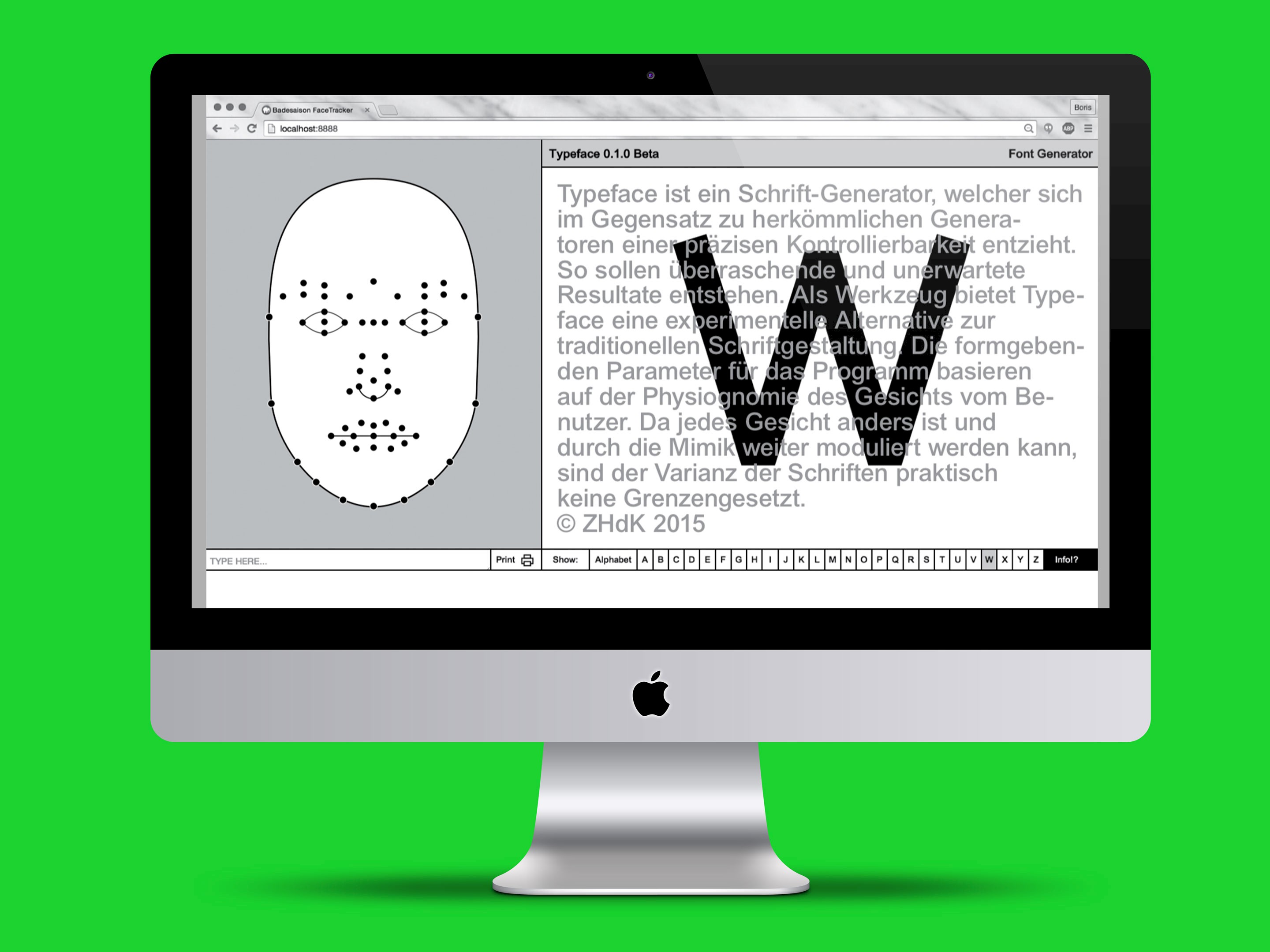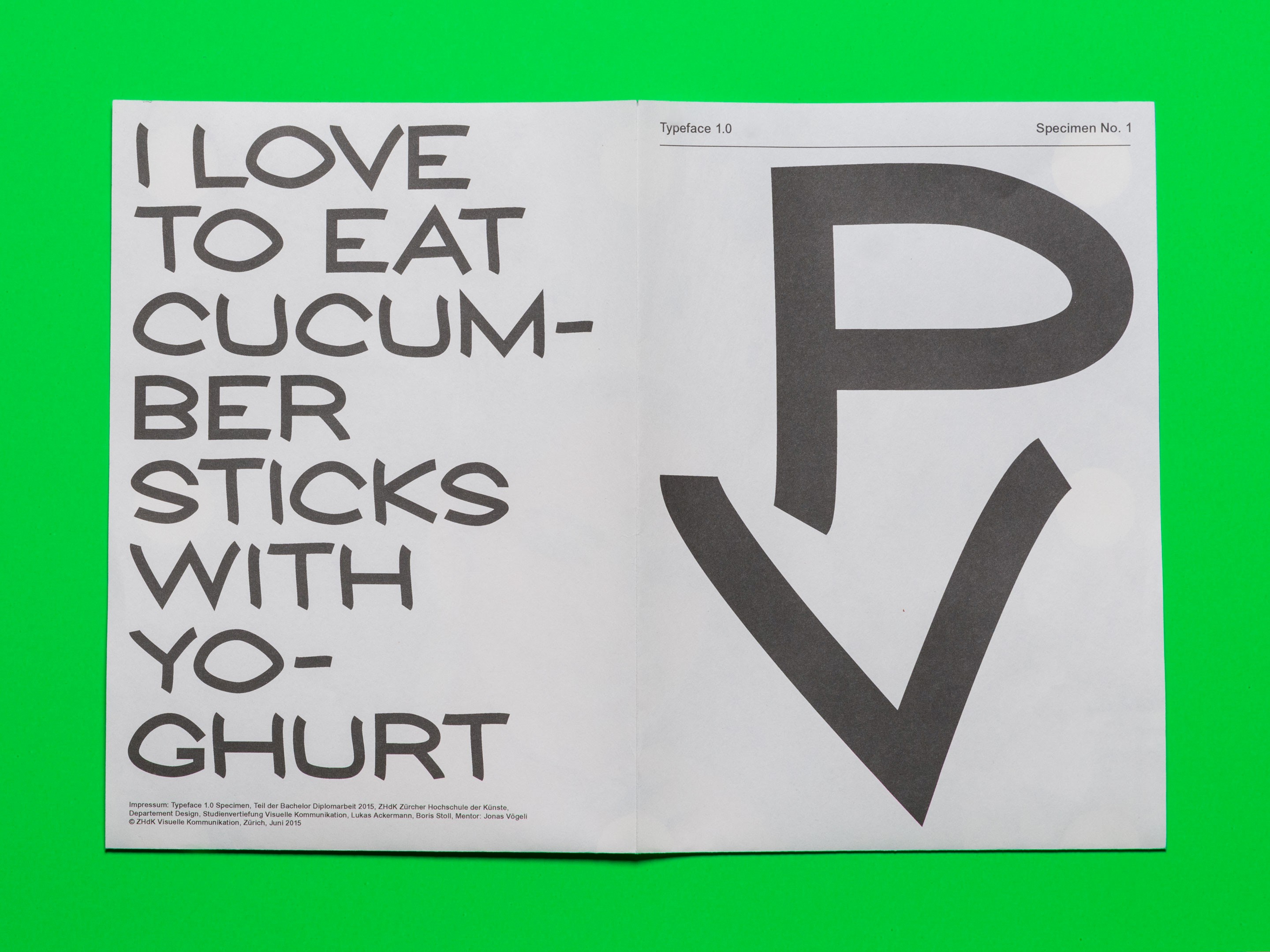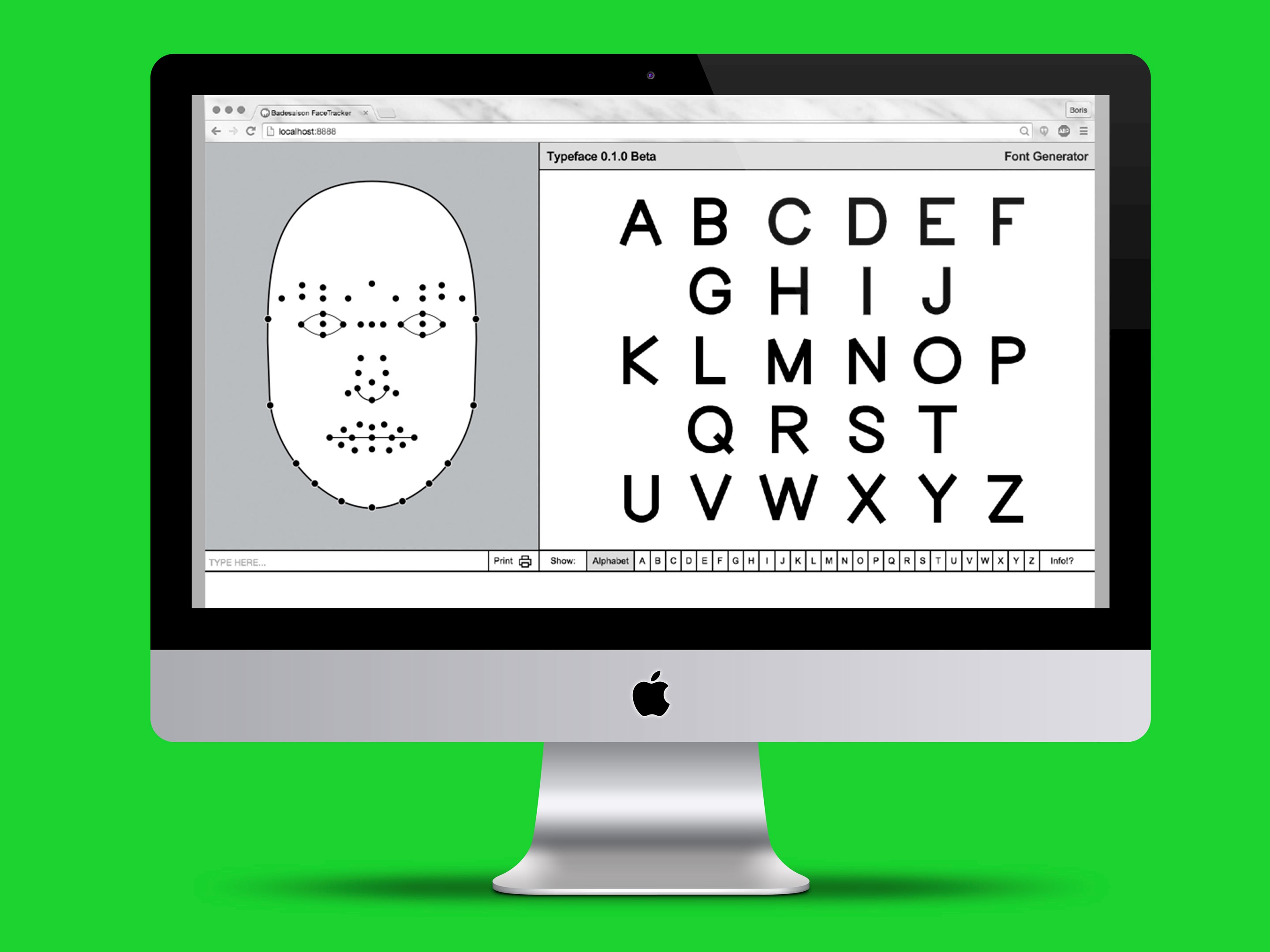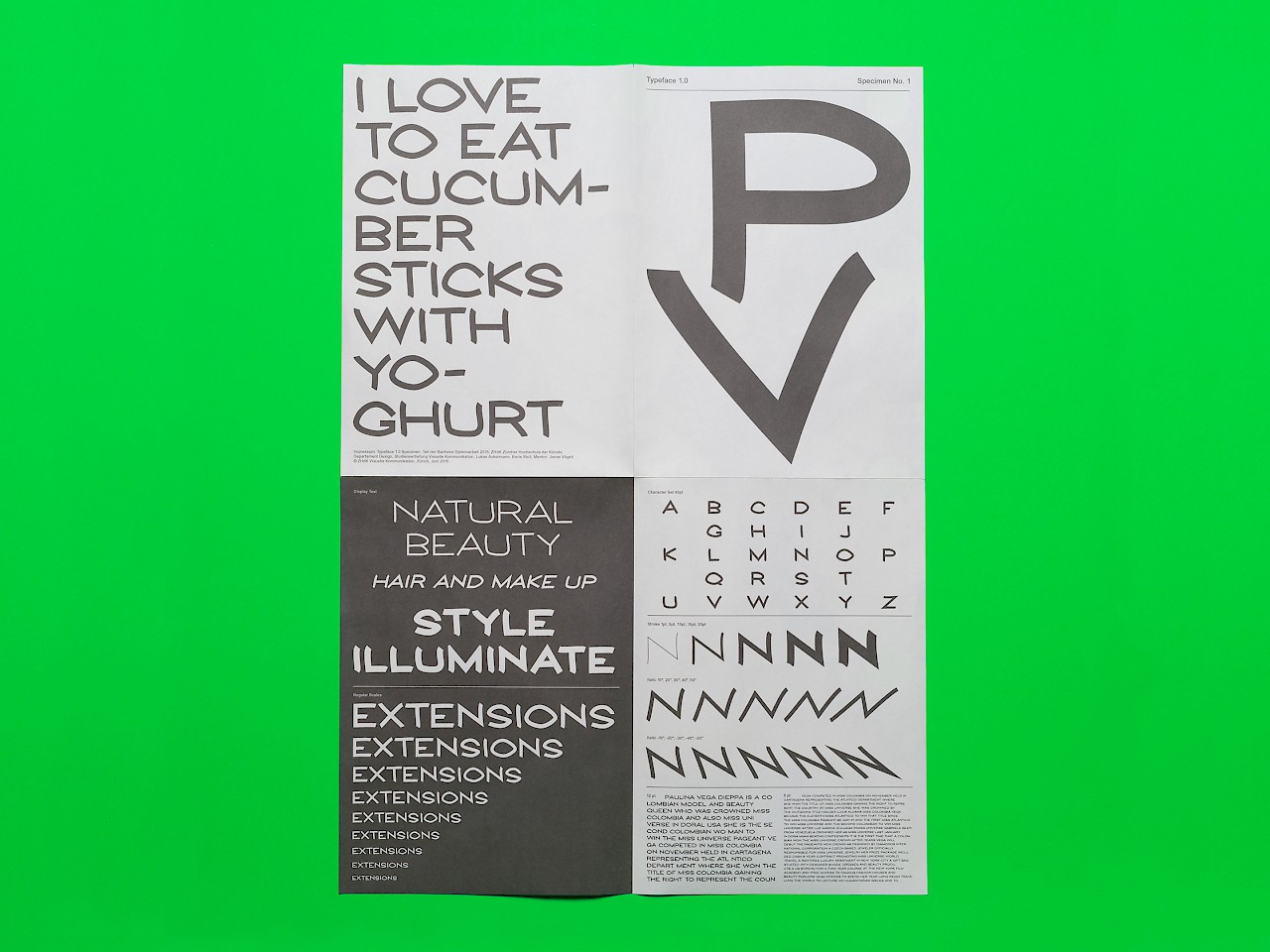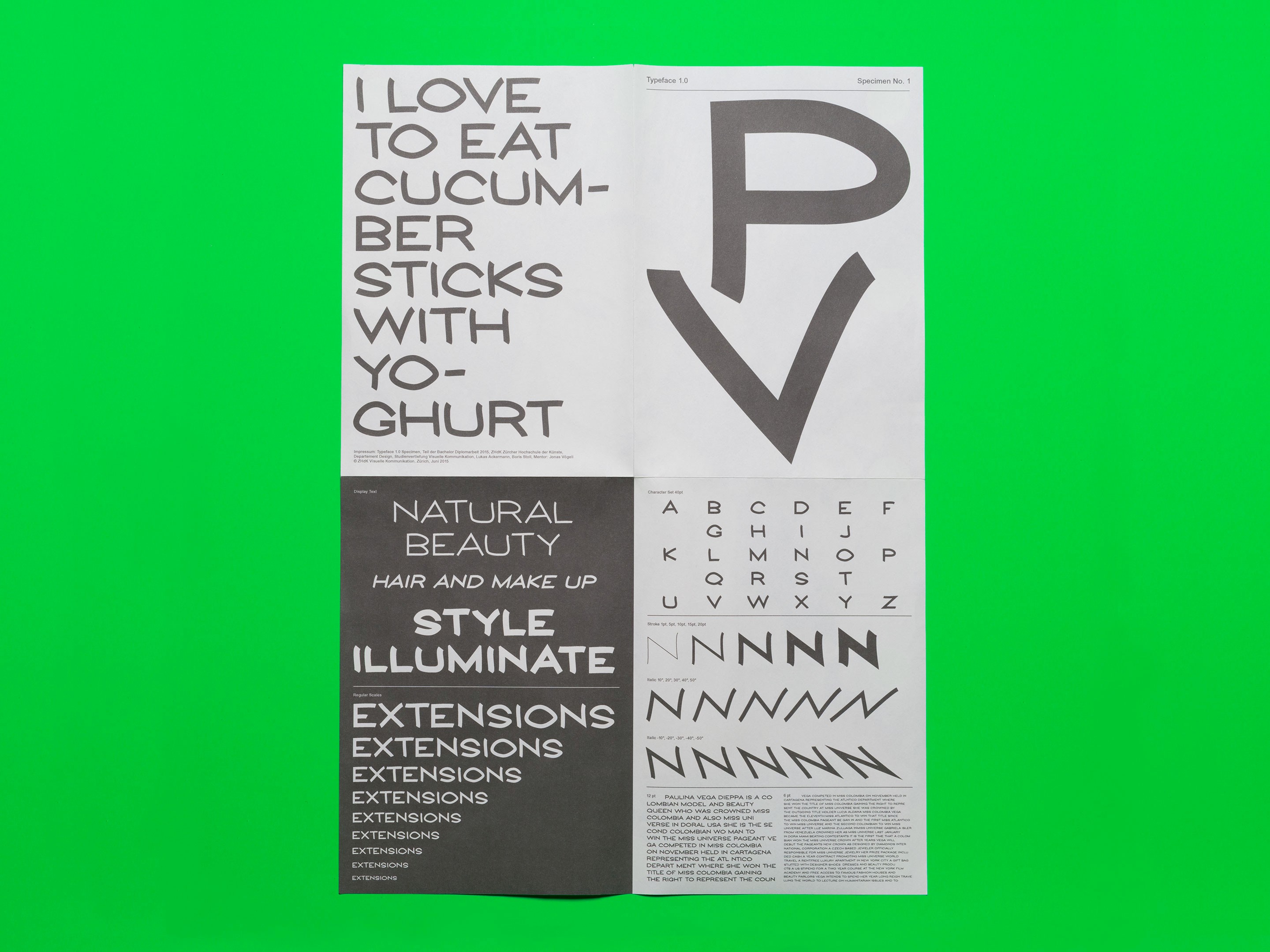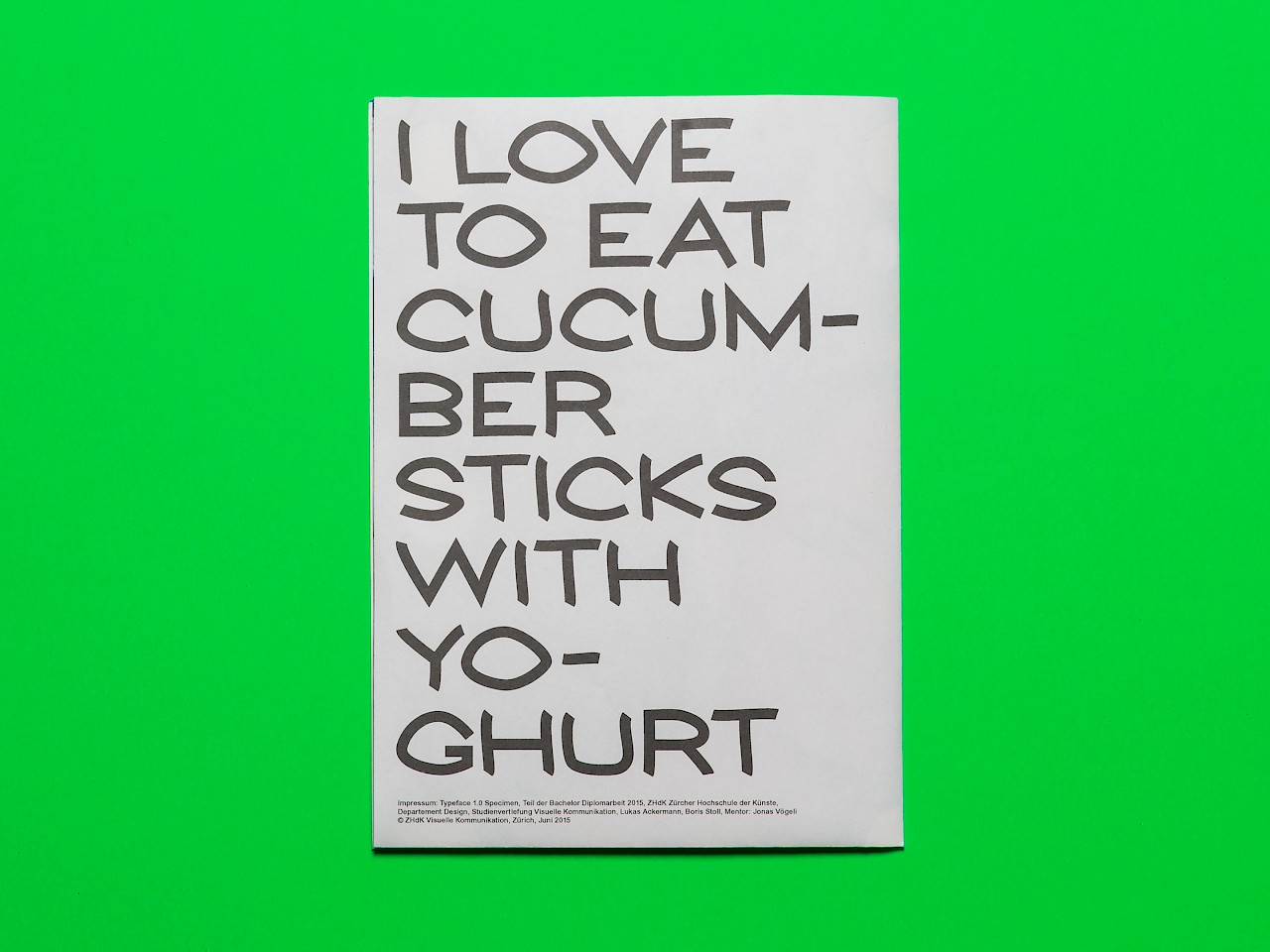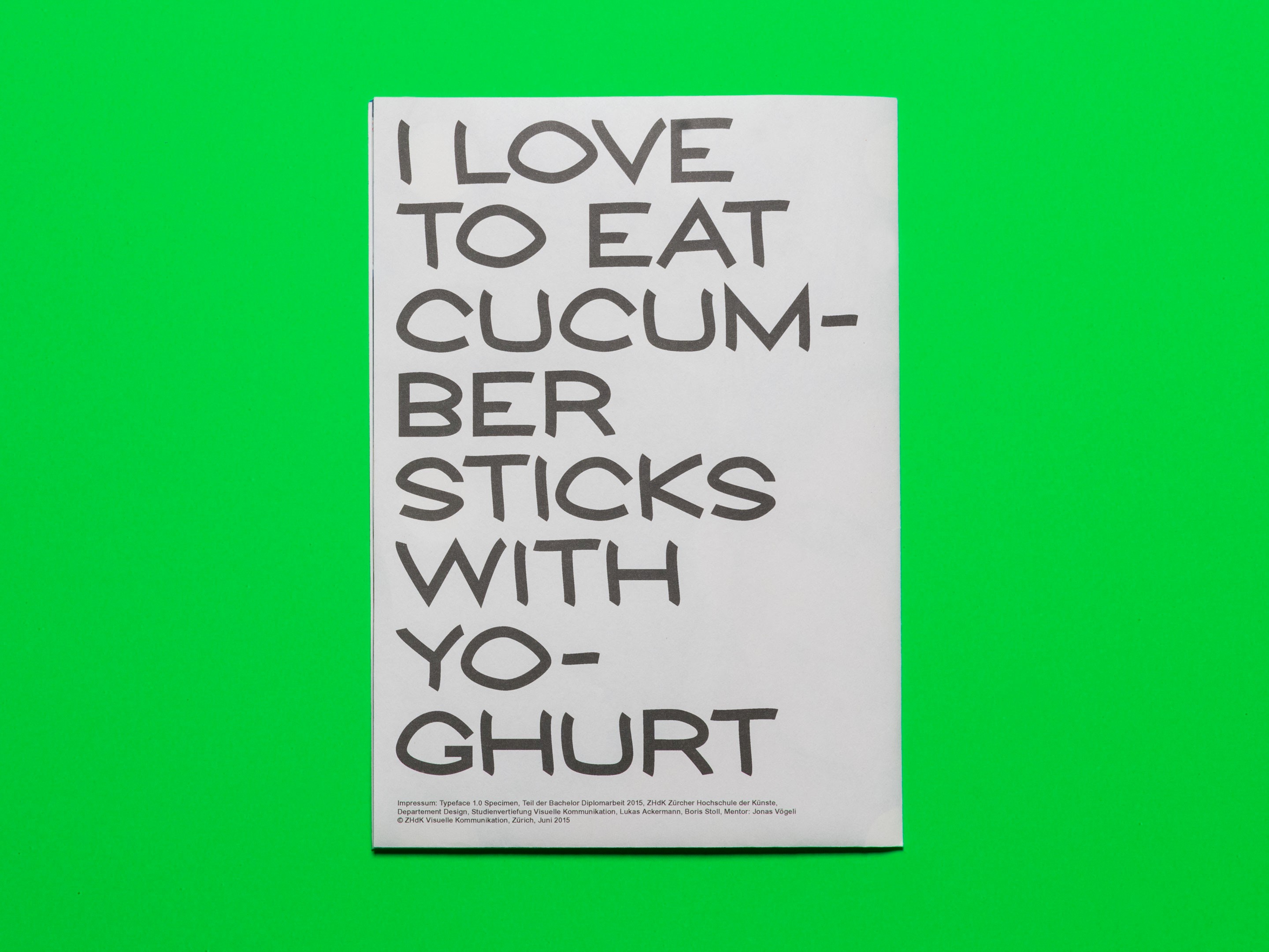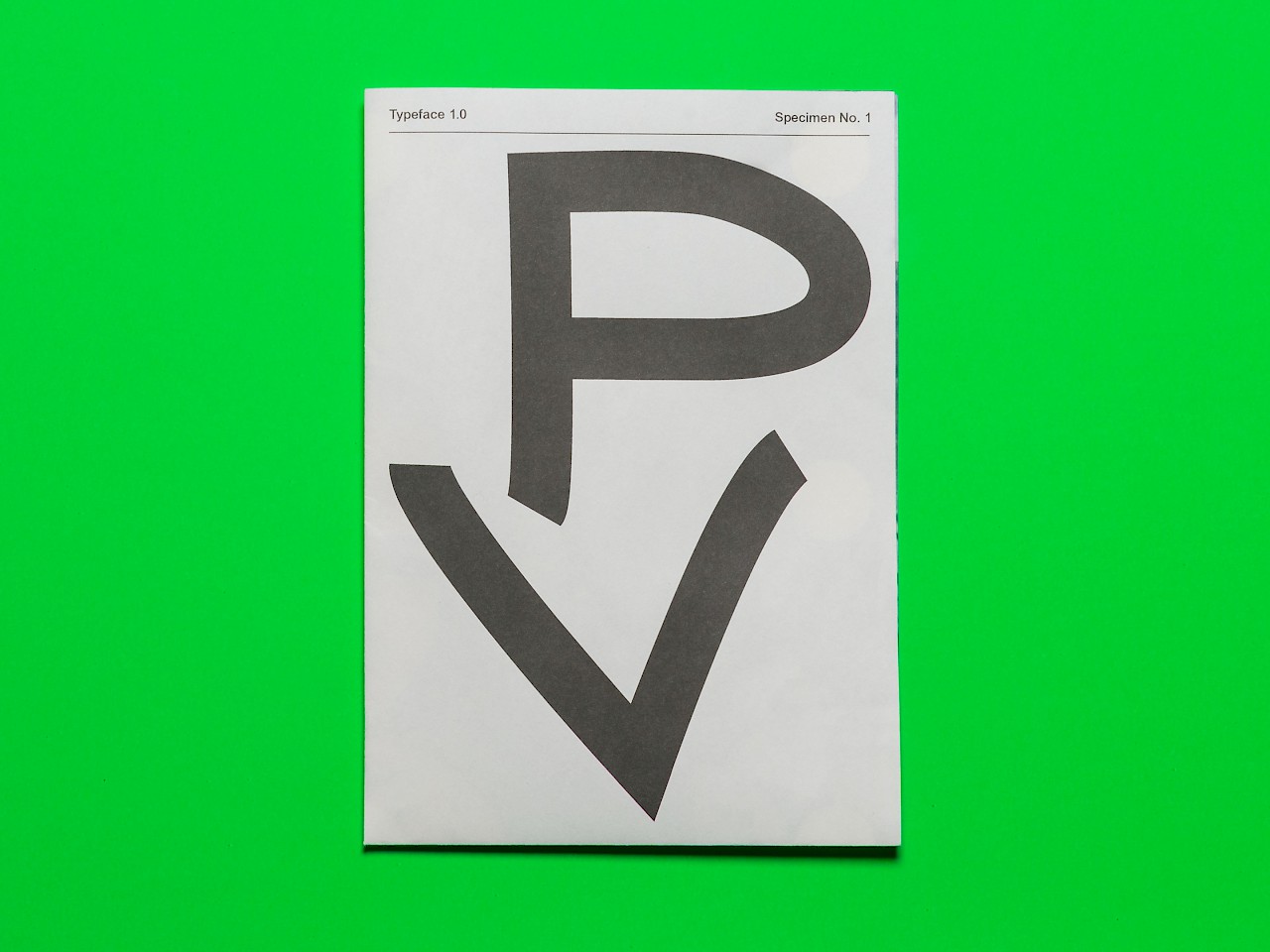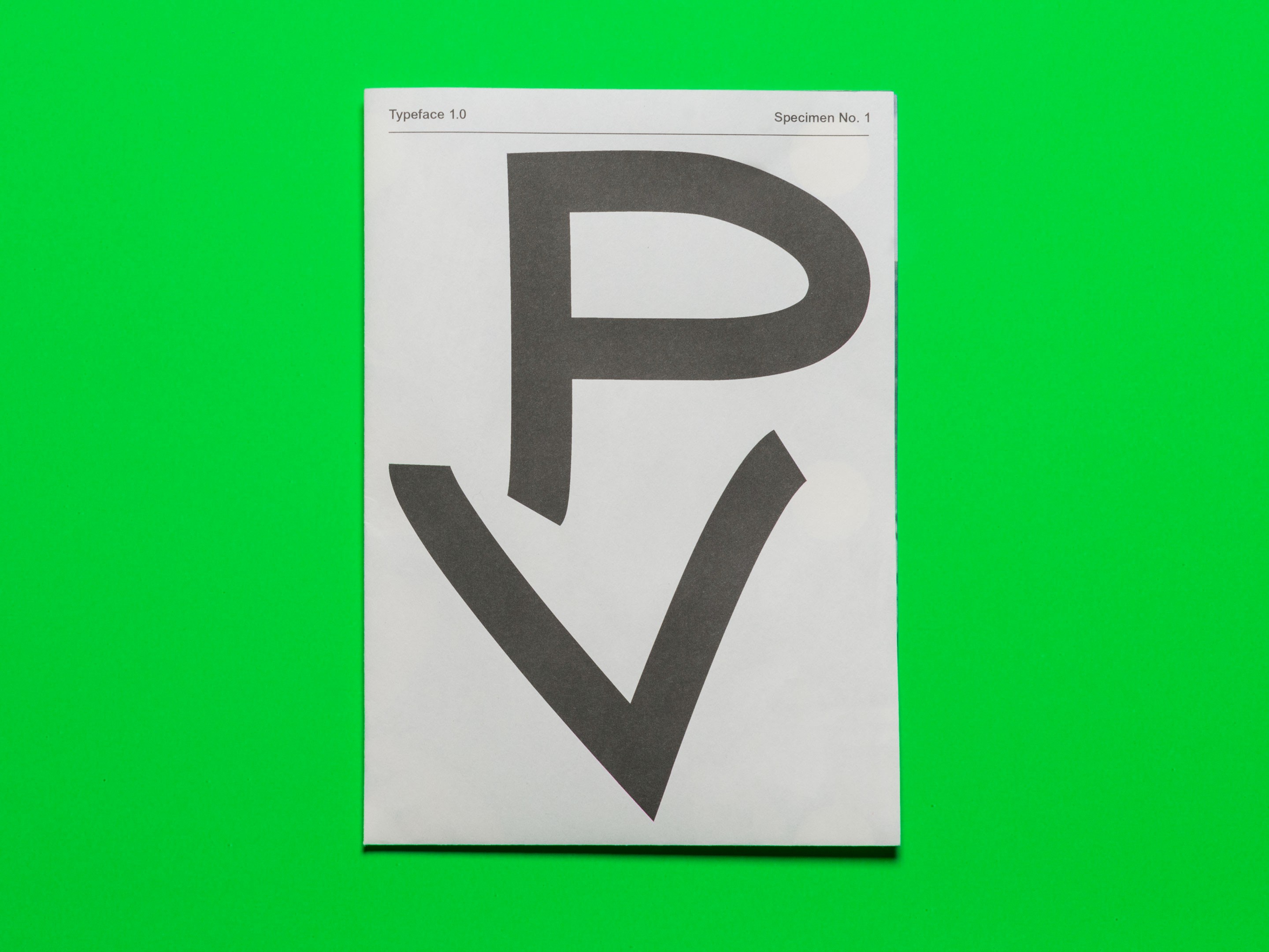
Typeface 1.0
Typeface ist ein Schrift-Generator, welcher sich im Gegensatz zu herkömmlichen Generatoren einer präzisen Kontrollierbarkeit entzieht.
So sollen überraschende und unerwartete Resultate entstehen. Als Werkzeug bietet Typeface eine experimentelle Alternative zur traditionellen Schriftgestaltung. Die formgebenden Parameter für das Programm basieren auf der Physiognomie des Gesichts des Benutzers. Da jedes Gesicht anders ist und durch die Mimik weiter moduliert werden kann, sind der Varianz der Schriften praktisch keine Grenzen gesetzt.